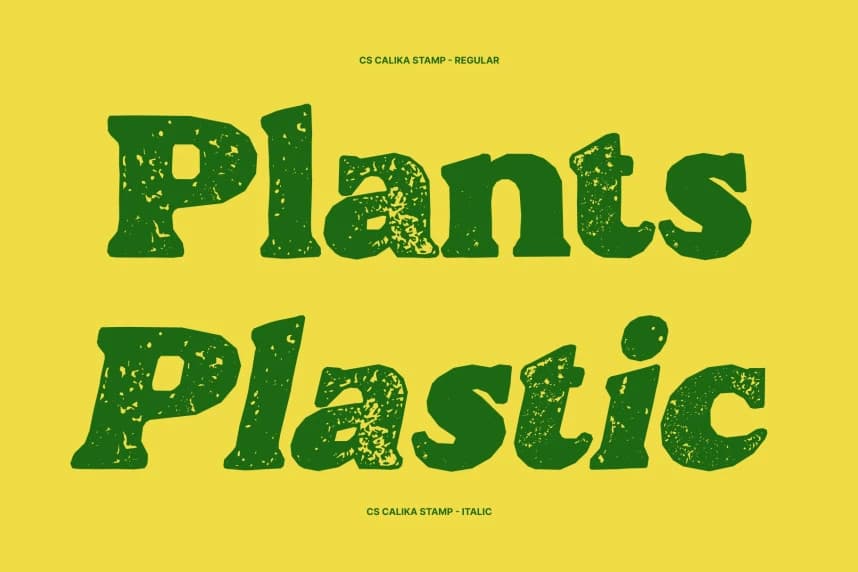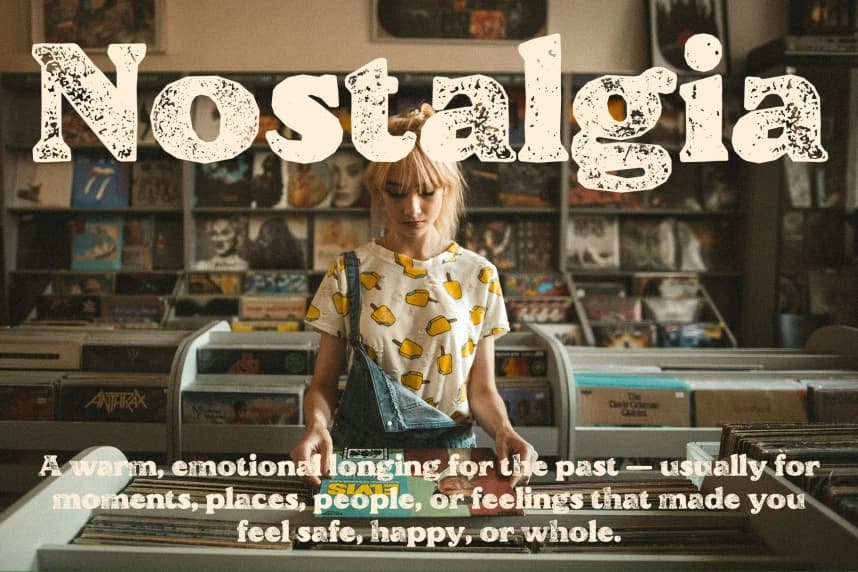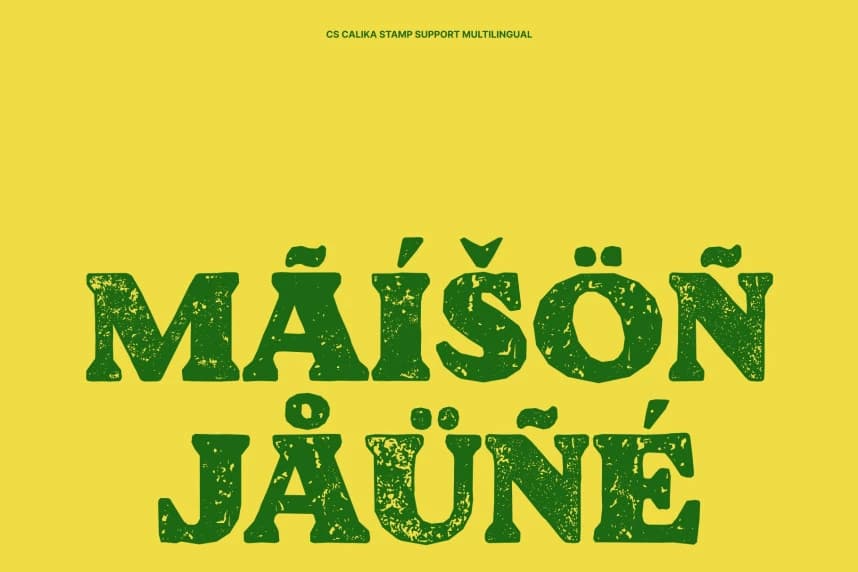
CS Calika Stamp Font
CS Calika Stamp Font – Vintage Damga Karakteriyle Retro Cesurluk, 90'lar Nostaljik Ruhu İçeren Kalın Serif Yazı Tipi. Bu, 1990'ların tasarımının canlı enerjisini yakalayan ve kendine özgü bir vintage damga etkisi sunan bir kalın serif yazı tipidir.
CS Calika Stamp Font – 90'ların nostaljik ruhuna sahip vintage damga karakterli kalın serif ile retro cesareti. Bu, 1990'ların tasarımının canlı enerjisini yakalayan ve belirgin bir vintage damga efekti sunan kalın bir serif yazı tipidir.